Képzési kreatív tipográfia "
Azt javaslom, hogy nézd meg néhány, a kivitelezett munkák egyike a tanfolyamokat. Feladata az volt, hogy felér, és tetszőleges összetételű a témában, kizárólag szöveges és font elemet.
Andrey Filimonov
Catherine Sosedova
A téma az első a két mű a hangszórót.
Ezen túlmenően, a hatás a felek csatolt szándékos deformációja karaktert és egy fokozatos változás színe sötétszürke fényes fehér. Az egyetlen neshriftovoy elem összetétele (bocs a kis megsértése feladatok) - Vízszintes választóvonal, amely található alsó harmadában a magassága a lap vizuális és létrehoz egy fejléc támogatás több betűt egy vízszintes felületre.
A második kompozíció alkotja szó Minden út dalszöveg, és ahogy a neve is mutatja, úgy tervezték, hogy társul az úton. Ez általában több statikus és kiegyensúlyozott, mint az előző, nem csak azért, hogy a centrális szimmetriatengelye, hanem amiatt is, hogy a fehér háttér. Mozgás itt vizuálisan felé a központ a lemez, majd - a frontális síkban felfelé. Ez a hatás úgy érhető nemcsak csökkenti a pont mérete, és a sortávolság (utánzás szempontjából), hanem amiatt is, hogy a fokozatos „fading” betűk. Az út, mintha „vége” ezekkel a szavakkal «elvezet» és mintegy harmada a magassága a lap, hanem felülről. Ez az arány (2/3) - az egyik legnagyobb harmonikusan által érzékelt ember.
Ami a fülhallgatót - akkor itt használjuk csak egy - KabelC könyv rendszeres, de itt néhány pár kellett küzdenie alávágási.
Melchakov Yuri
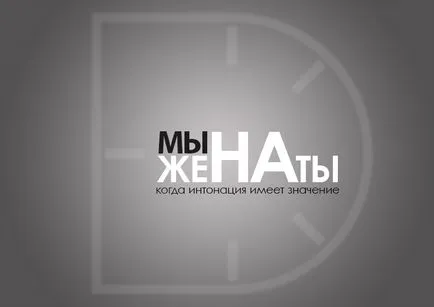
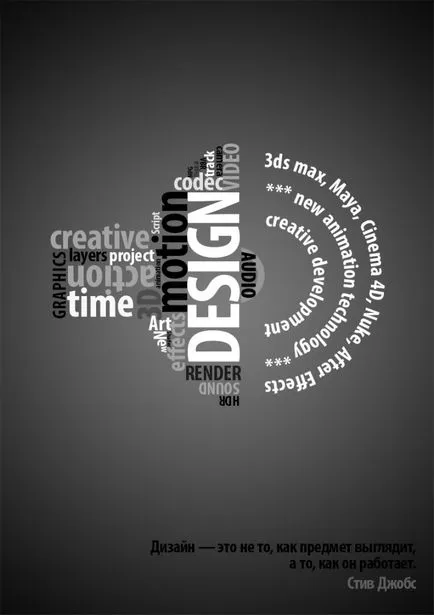
Gulyaev Irina
Saját készítmény KEEP - távolság egy változata a téma a „fehér holló” .A központ - a „a” betű, ami meglehetősen eltérnek közé. Ők nagyobbak, szimbolizálja agresszió fejét. TARTSA távolsági vonalak úgy vannak elrendezve, hogy pont a közepén a kompozíció. Ez a fajta egy nyíl vagy egy fegyvert, amelynek célja az irányt az idegen.
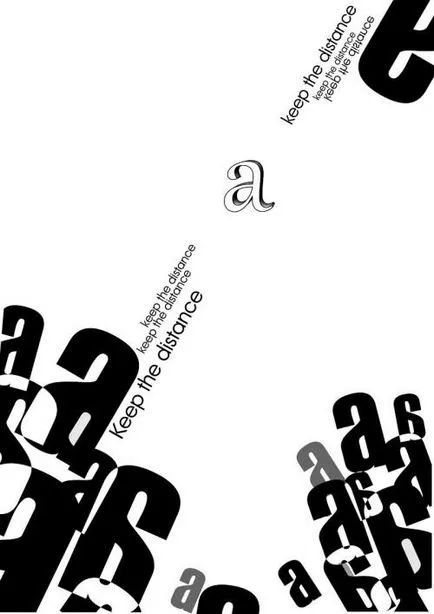
Mert az ő második készítmény, vettem a sorban, és vékony. irodalomban. Az általános hangulat - lírai. Annak érdekében, hogy ezt hangsúlyozni, én választottam a forgatókönyvet. Ő, ellentétben Antiqua és groteszk kevésbé formális. Sőt, hozza egyfajta személyes kapcsolat, dushevnosti.Voobsche, a kifejezés szavakkal kezdődik VÉGE zuhany. Nem tudom, hogy tesznek-e, hogy ebben a prezentáció kényelmes. Úgy érveltem: felhőszakadás - ez az erő, elem, amely képviseli a zavart, a félelem, részben valaki másnak a könnyek. Ezért volt szükség ahhoz, hogy ezeket a szavakat a megfelelő típust. De! Másrészt, vége volt, és ez a fontos! A levegő, már csak a köd - ez egy újjászületés jelképe, a feltámadás kezdeni jobb! Ezeket a szavakat kell tenni könnyű, érzés, a „levegő” és a „könnyű”. Mintegy bukovki - mint cseppek eső vagy köd. Nem tudom, ha én, hogy negatív teret dolgozni létrehozására dinamika, vagy sem sikerült.
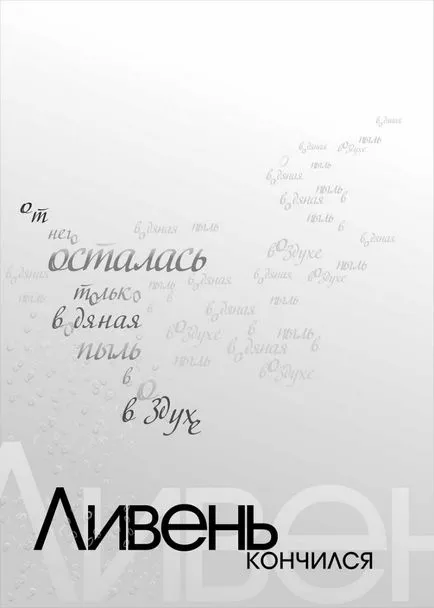
Sutuga Olga
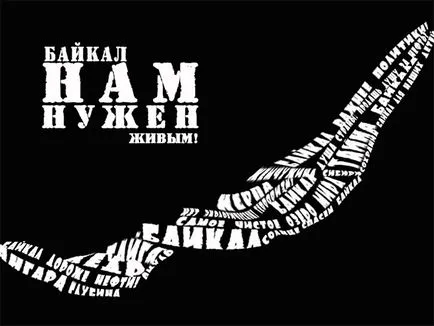
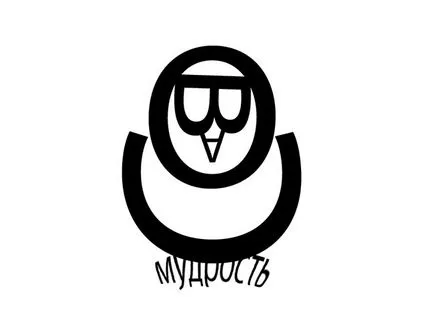
Churzin Alina
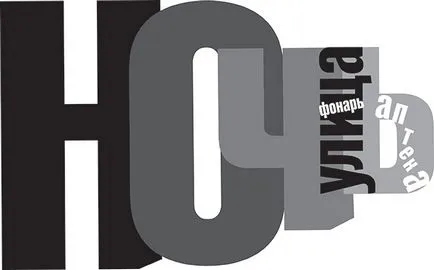
tatiana Chzhan
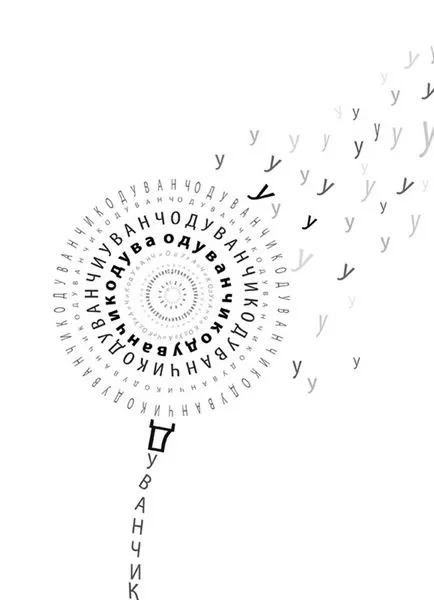
Catherine Yatskova
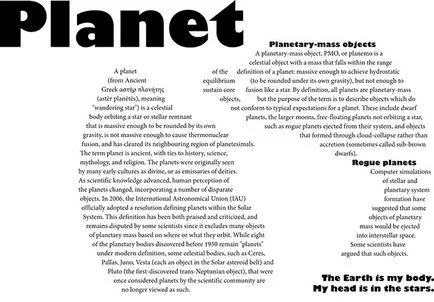
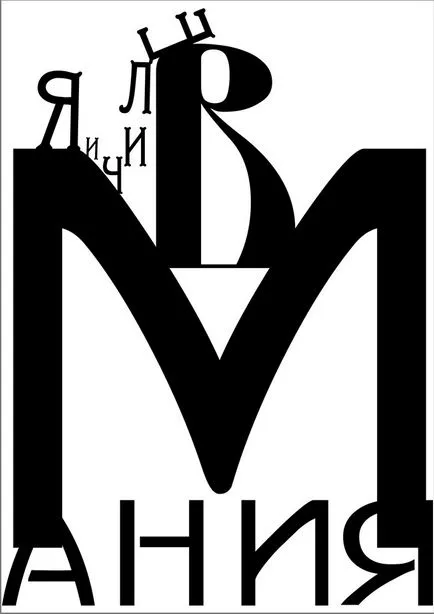
Tárgy: „megalománia”.
Én egy fekete háttér, mint a fő célja a „B” úgy tűnik, hogy a legelőnyösebb és kifejező, mint a fehér. Hangsúlyozni a nagyságát a „B” használt része a B betűvel „Jelic” A leveleket írt része a B betű, mint egy tartályba, és az utolsó betű, a szó „nagyság”, „I” - egy betű egy szó a „mánia” és a „nagyság”. A „mánia” meg van írva a használata negatív térben. Ha továbbra is az ütemes sorozat, valamint a nagyobb kompozíciós stabilitást a megismételt „I”, vagy inkább a negatív tér, a fekete-fehér.
Delver Elena
Shipov Aleksey